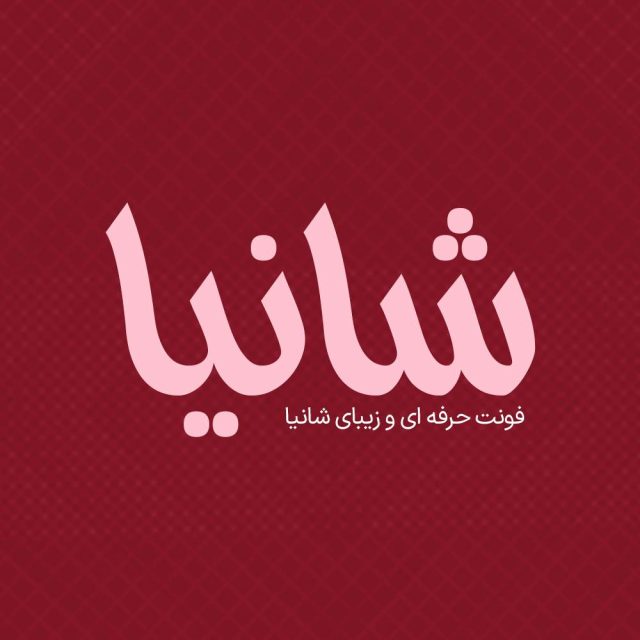
فونت فارسی شانیا Shaniya Font
فونت فارسی شانیا یک فونت نمایشی است که شخصیتی جسور، خلاق و مستحکم دارد. فونت فارسی شانیا برای عناوین و سطرهای کوتاه طراحی شده و با وجود جدیت و استحکامش، دلنشین است. فونت شانیا انتخابی ایده‌آل برای تیترها، عناوین، متن‌های کوتاه، فضای تبلیغاتی و شبکه‌های اجتماعی است. این فونت با ساختار حروف خود مناسب استفاده در لوگوهای نوشتاری می باشد. همچنین از این فونت در طراحی تابلوهای چلنیوم هم به دلیل ساختار منحصر به فردش می توانید استفاده کنید. در ادامه برای شما نمونه تایپ های این محصول حرفه ای رو آماده کردیم که میتونید مشاهده کنید.
• مناسب طراحی بسته بندی ها و چاپ
• فونت ویژه تبلیغات محیطی
• فونت طراحی کاور اینستاگرام
• فونت حرفه ای برای تولید محتوا
• فونت فارسی طراحی وبسایت
• فونت طراحی لوگو تایپ فارسی
• مناسب استفاده در تابلو های چلنیوم و طراحی حروف
پیشنمایش و نمونه تایپ های فونت شانیا